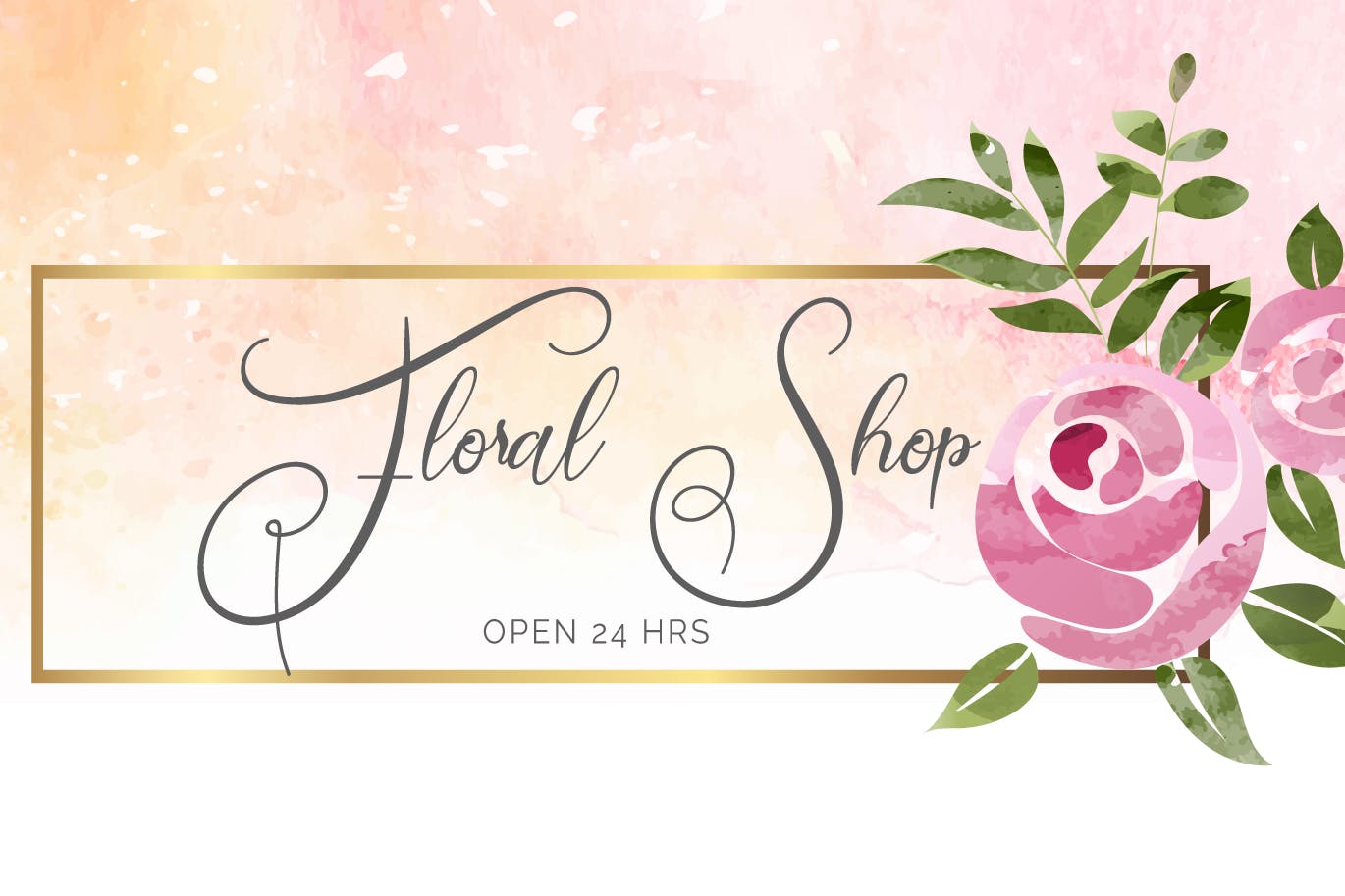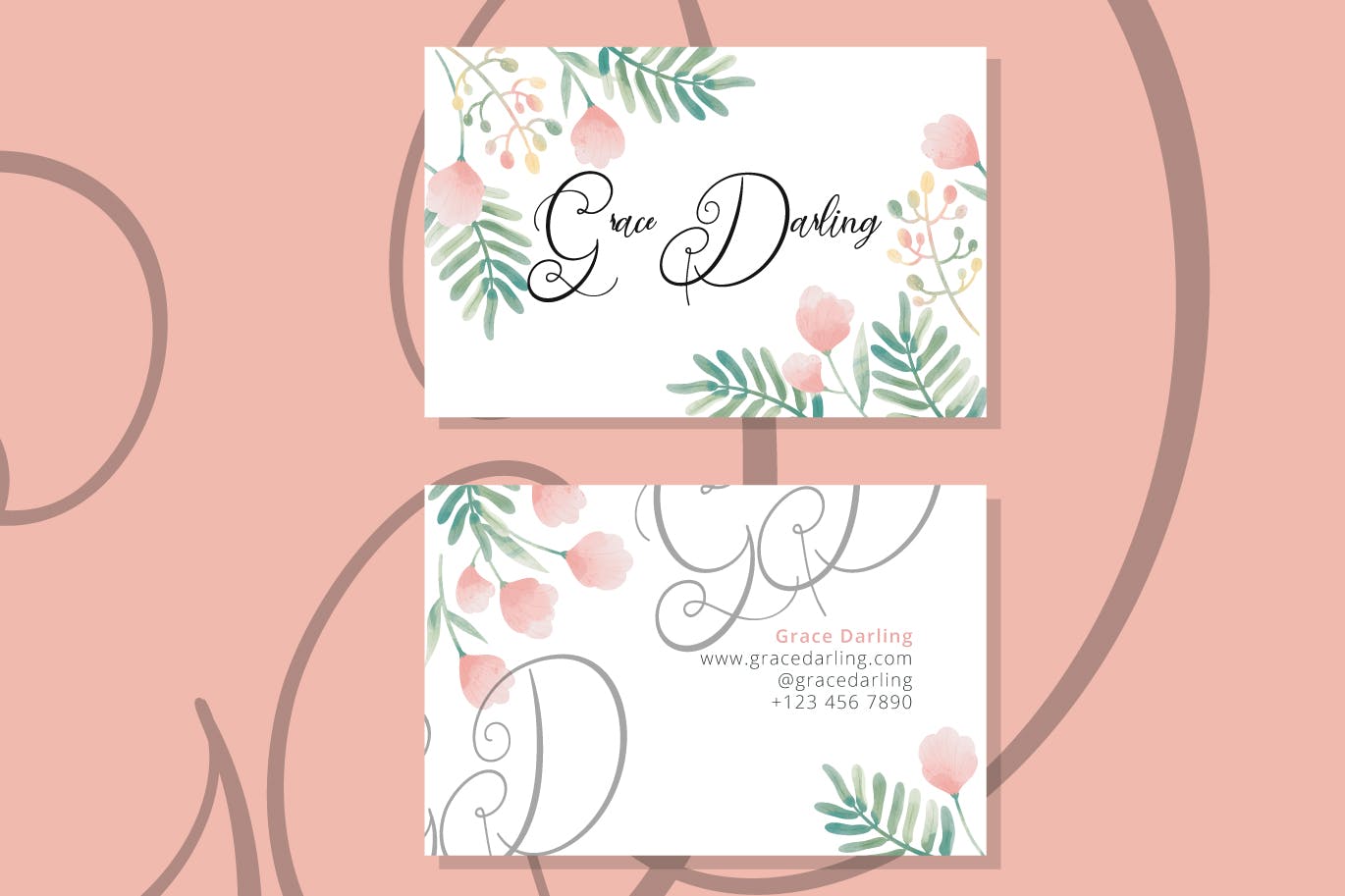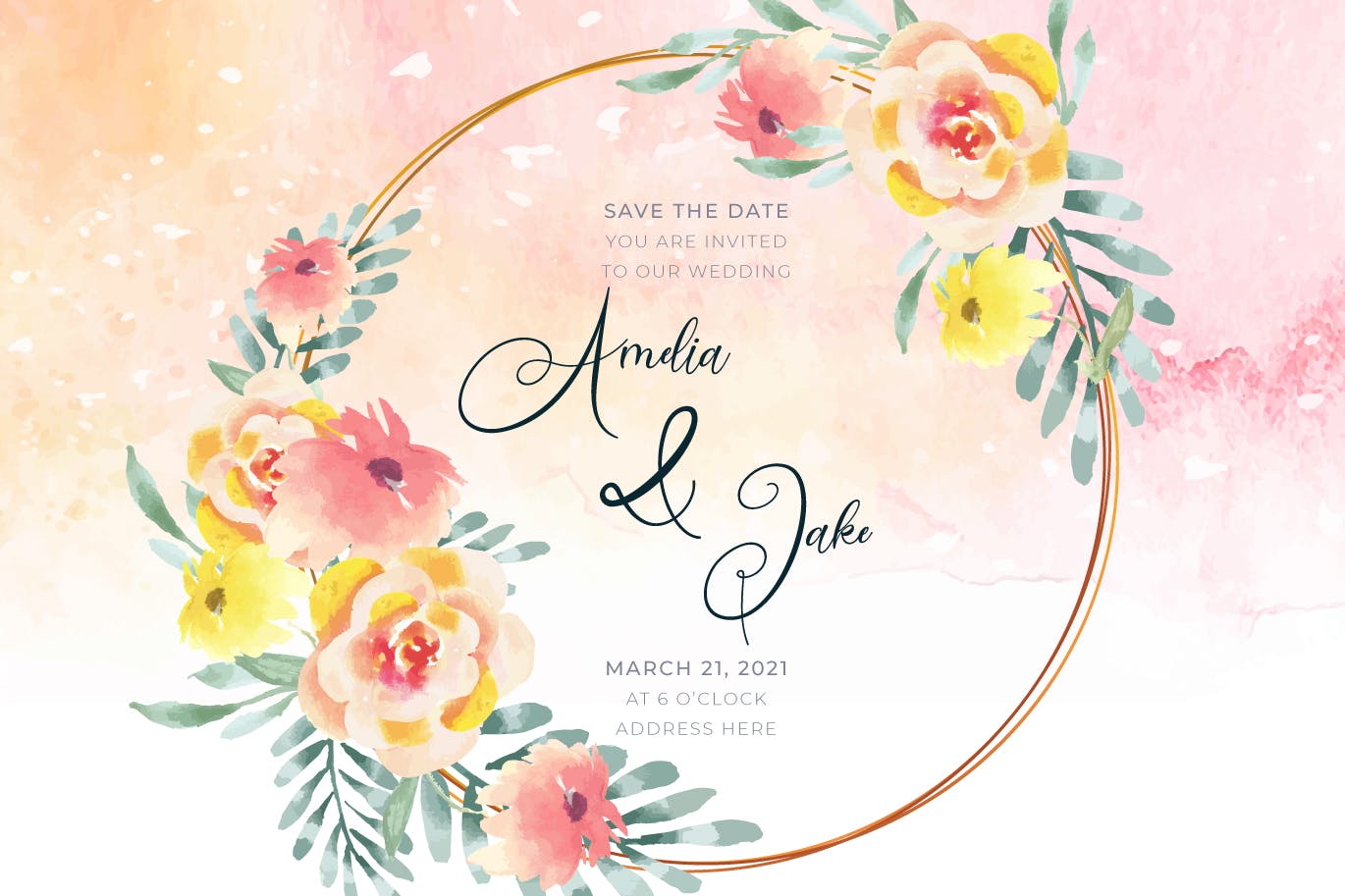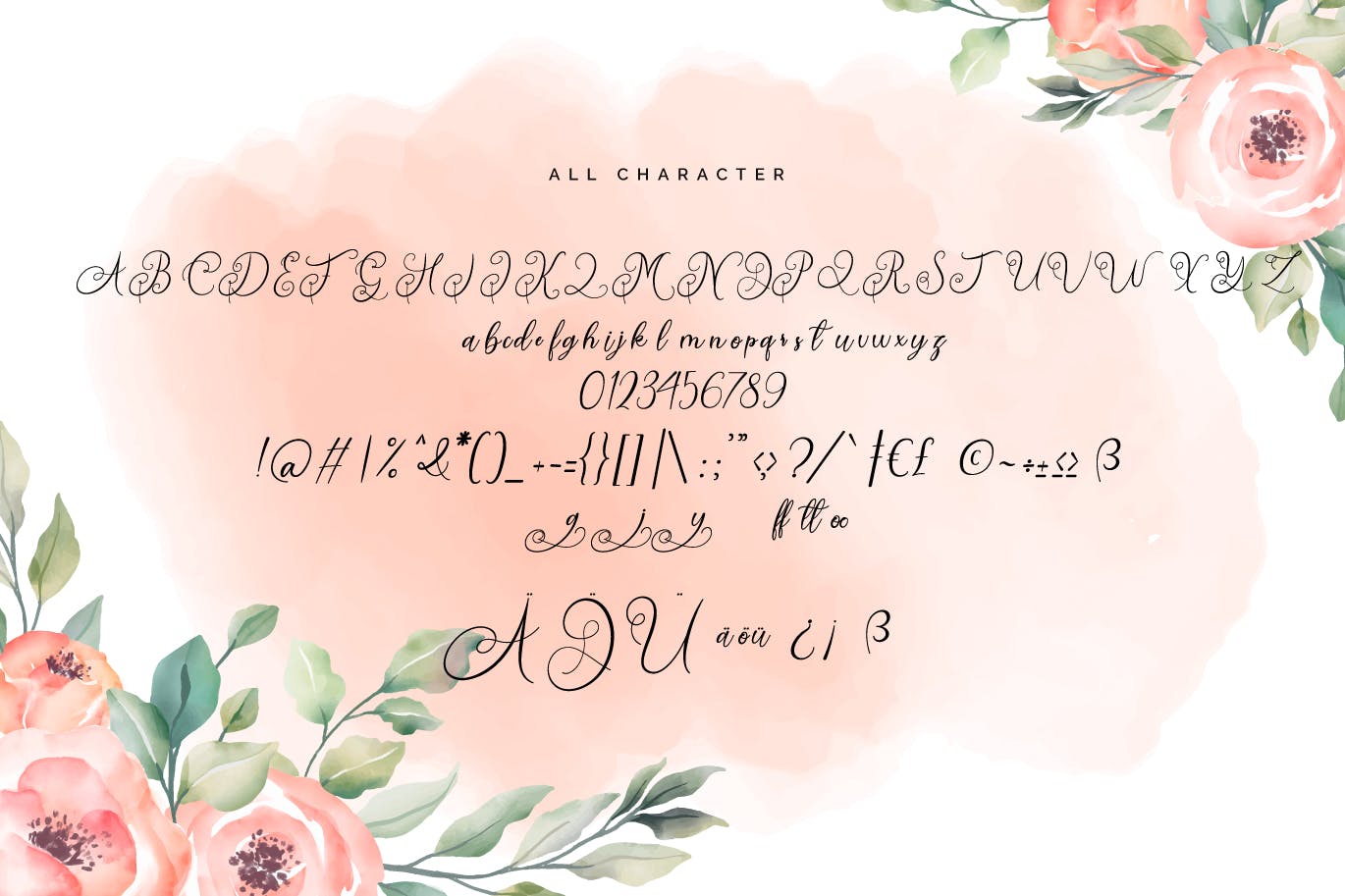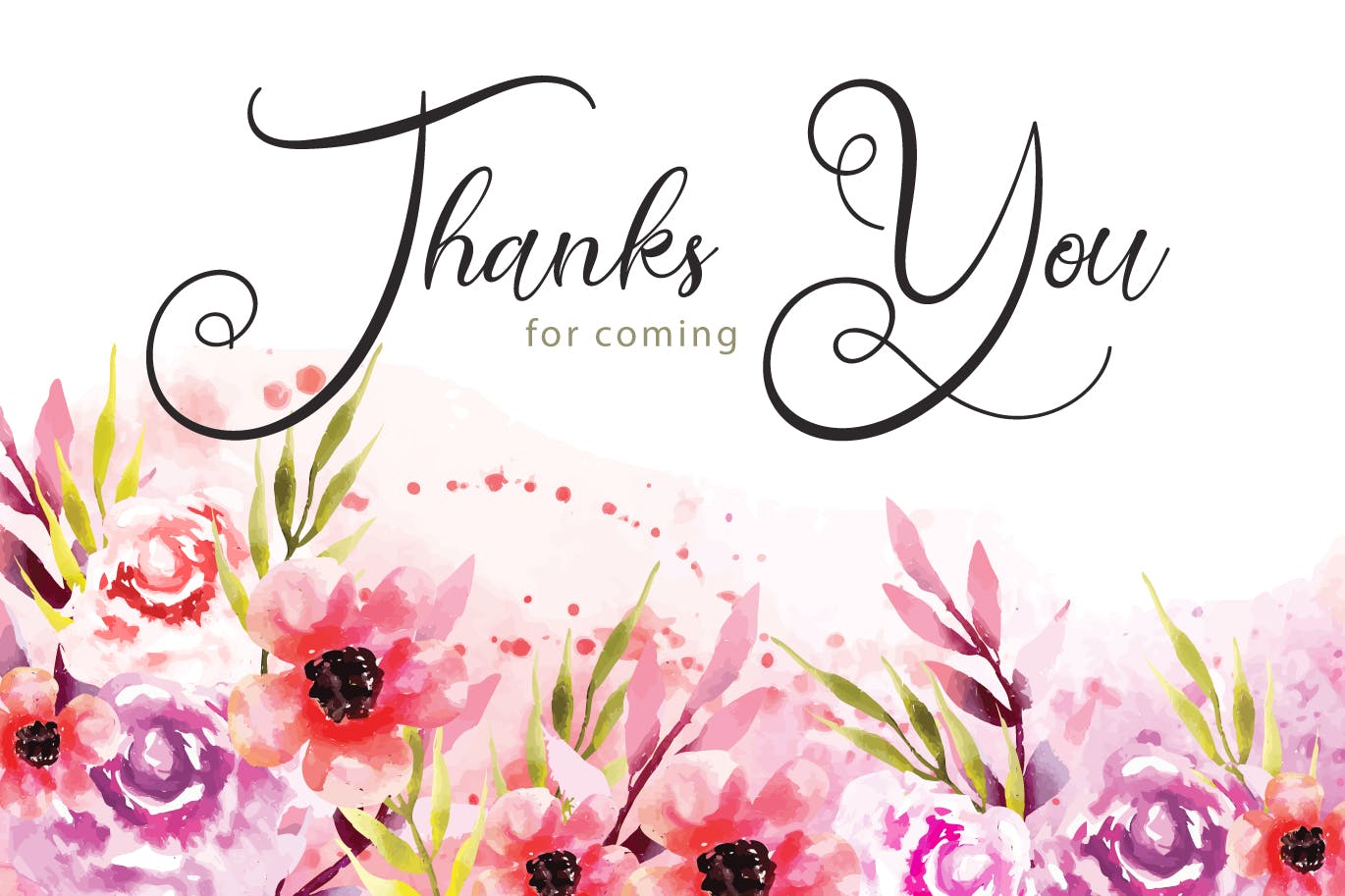
Quirtty | فونت اسکریپت لوکس با سبکی خوشنویسی، بسیار زیبا برای استفاده در دعوتنامهها، کارتهای تبریک، مواد برندینگ، کارتهای کسبوکار، نقل قولها، پوسترها و موارد دیگر!
کاراکترهای جایگزین به چندین ویژگی Open Type تقسیم شدهاند، از جمله ستهای سبک، جایگزینهای متنی، SWASH و Ligature. ویژگیهای Open Type را میتوان با استفاده از برنامههای حرفهای مانند Adobe Illustrator، Adobe InDesign، Adobe Photoshop Corel Draw X و Microsoft Word دسترسی پیدا کرد. این فونت دارای کدگذاری PUA Unicode است (فونتهای مخصوص کدگذاری شده) تا تمام کاراکترهای جایگزین بهراحتی در دسترس باشند.